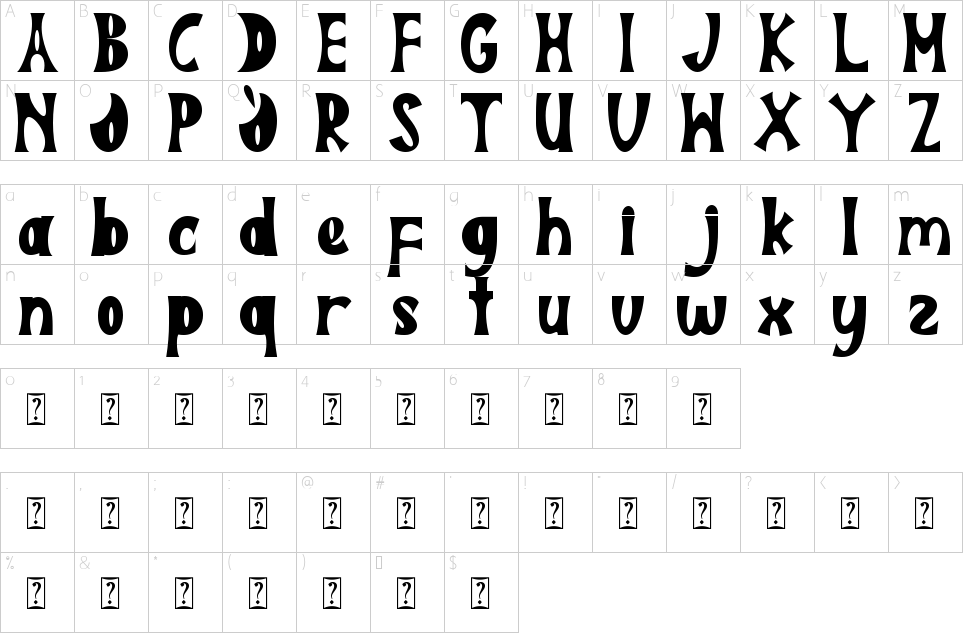
A fonte ‘Panorama Balinesia Font’ é uma criação cuidadosamente pensada pela Yoga Letter, disponível gratuitamente tanto para sistemas Windows quanto para Mac. Com seus traços fluidos e elegantes, essa fonte traz um toque de sofisticação ao seu design, tornando-a perfeita para aplicativos de texto, design de sites e muitos outros projetos de design. Se você está buscando um recurso gráfico versátil e de alta qualidade, a ‘Panorama Balinesia Font’ é definitivamente para você. Desenvolvida com cuidado, esta fonte tem sido baixada 321 vezes, uma indicação de sua qualidade e popularidade. Engane-se se acredita que é uma fonte comum. ‘Panorama Balinesia Font’ é uma jóia para seu portfólio de fontes.